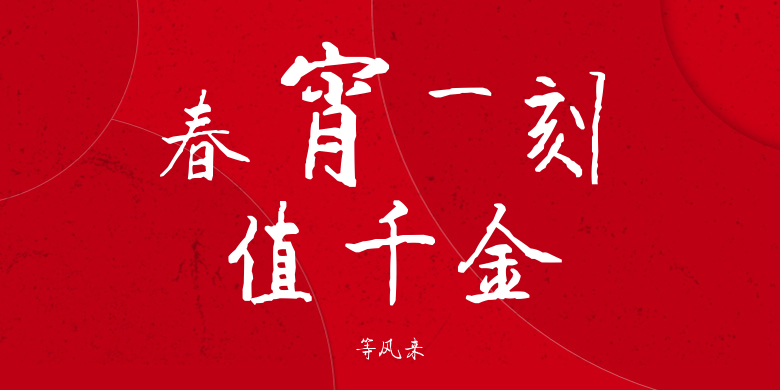
等风来
等风来,这款字体结构工整、笔画清晰,兼顾美观与易读性,适用于标题、正文、海报、包装、LOGO 等多种场景。字形优雅稳定,风格百搭耐看,适配日常排版与创意设计,让文字呈现更舒适、更具质感。等风来一笔一画,皆是细节,以均衡的比例、流畅的线条打造舒适视觉体验,字形端正大气,风格简约现代。无论是商业设计、品牌宣传还是日常排版,都能轻松驾驭,让文字更有格调与力量。等风来字体下载。